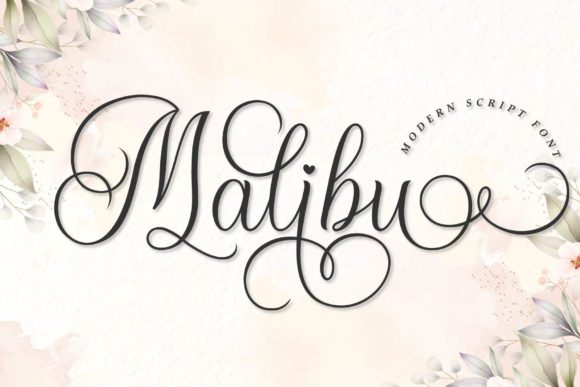
Creativefabrica Malibu Font
[Creativefabrica] Malibu Font
Малибу - это элегантный рукописный шрифт.
Влюбитесь в его невероятно универсальный стиль и используйте его для создания эффектных дизайнов!